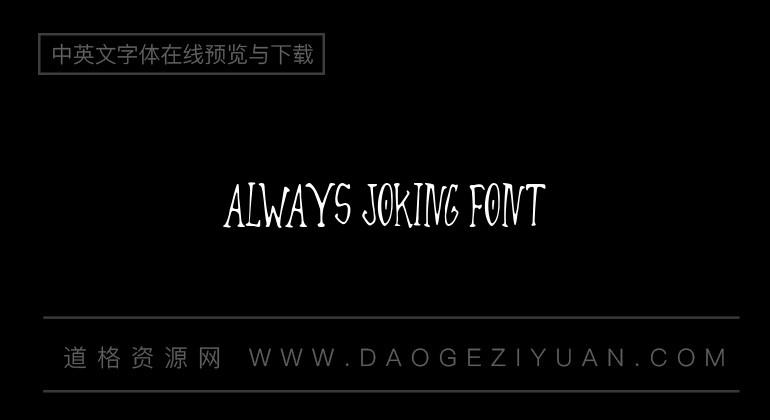
Always Joking Font 是一种手写风格的字体,它呈现出轻松、有趣的氛围,适合用于制作海报、宣传资料、贺卡等设计项目。这种字体的特点是字母间距宽松、笔画粗细不同、字母形状扭曲,显示出一种故意夸张的风格。常用的颜色是黑色和白色,但也可以根据设计需要进行调整。Always Joking Font 可以在许多设计软件中使用,如 Adobe Photoshop、Illustrator、InDesign 等,它是一个不错的选择,可以帮助您创造出个性化的设计作品。内容介绍
Always Joking Font是一款非常不错的手写艺术字体,具有很好的视觉感,适合于文化类的宣传设计、商业类品牌的广告和产品包装设计以及个性化文字排版等较多场景。